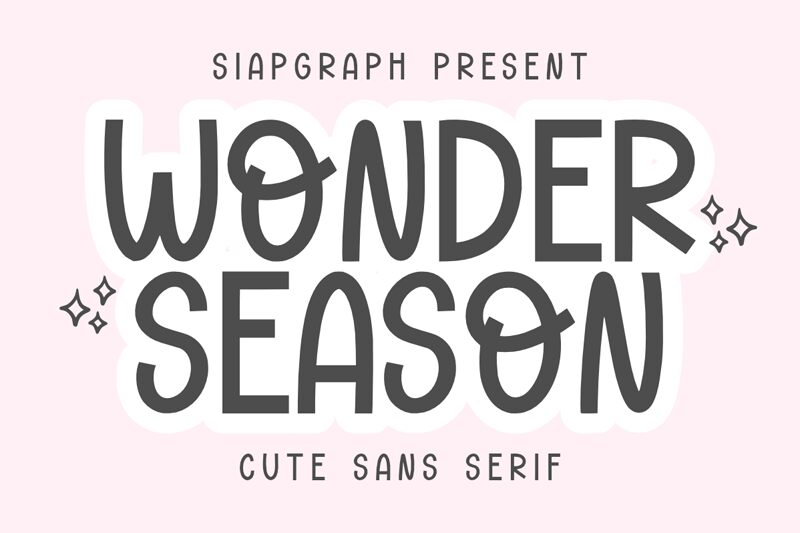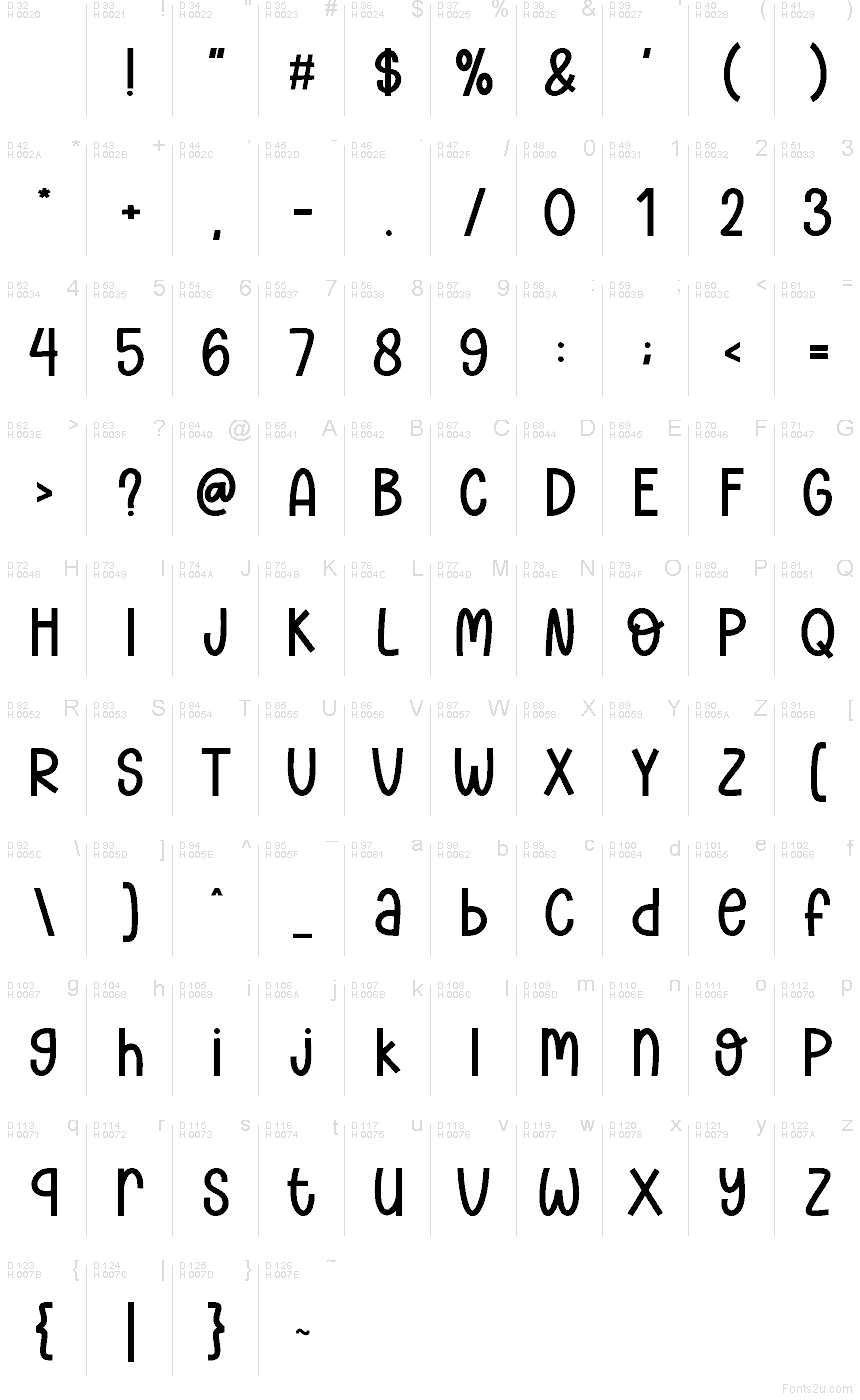
Wonder Season Regular
Wonder Season od SiapGraph je bezplatné písmo typu display, ktoré charakterizujú vysoké, zaoblené ťahy a hravý rytmus, akoby vystrihnutý rukou. Písmená majú hladkú, otvorenú konštrukciu, no vďaka meniacej sa výške a jemným krivkám pôsobí dizajn uvoľnene a veselo, pričom sa vyhýba prísne geometrickej strohosti.
Tento nepravidelný rytmus skvelo vynikne na obaloch butikových produktov, v kaviarenských menu, na sezónnych plagátoch, v hlavičkách na sociálnych sieťach alebo v hravých logách, kde by bežné bezpätkové písmo pôsobilo až príliš obyčajne. Krátke nadpisy obzvlášť profitujú zo živej siluety tohto fontu, ktorá dodáva každému riadku priateľský charakter bez toho, aby skĺzla k samoúčelnému dekoru.